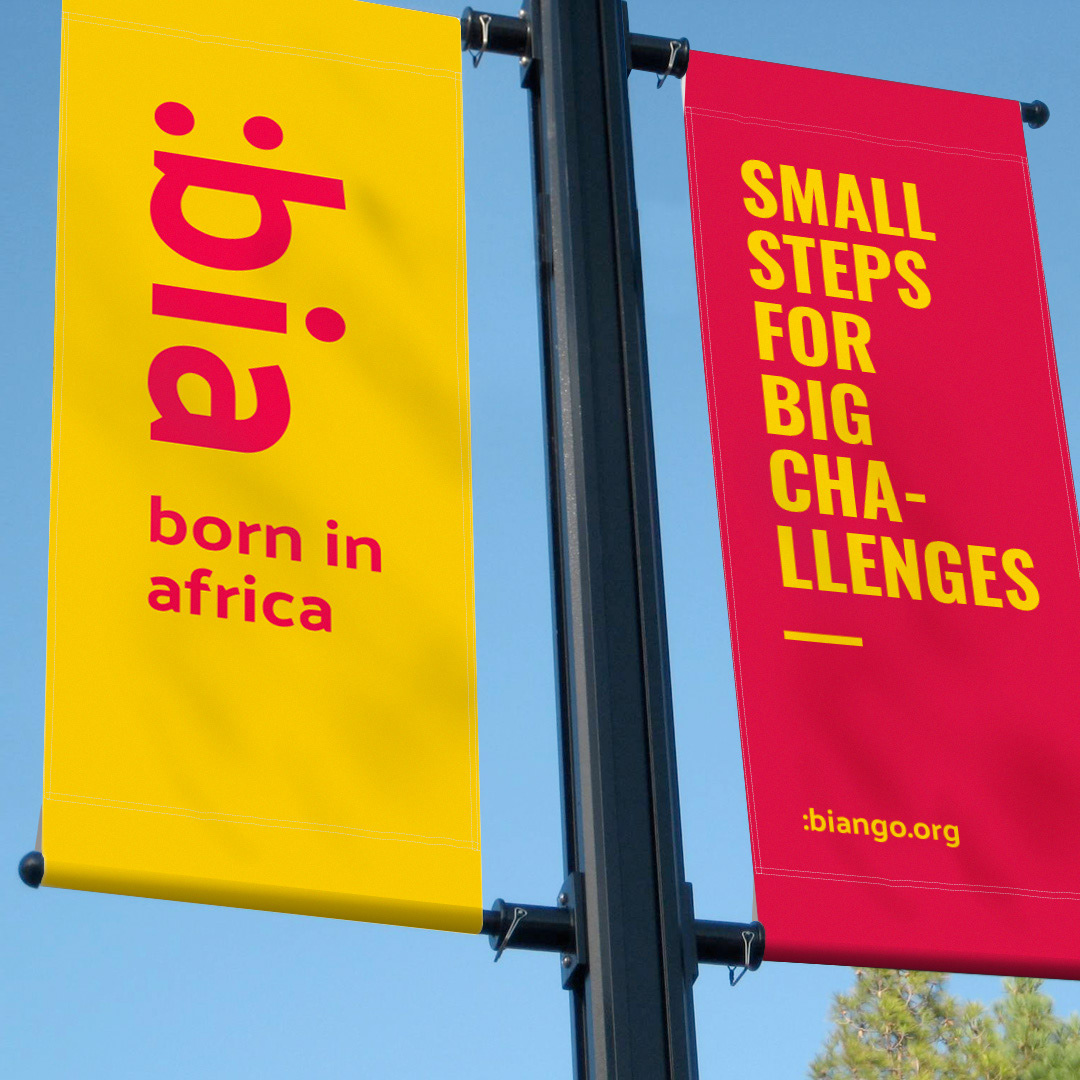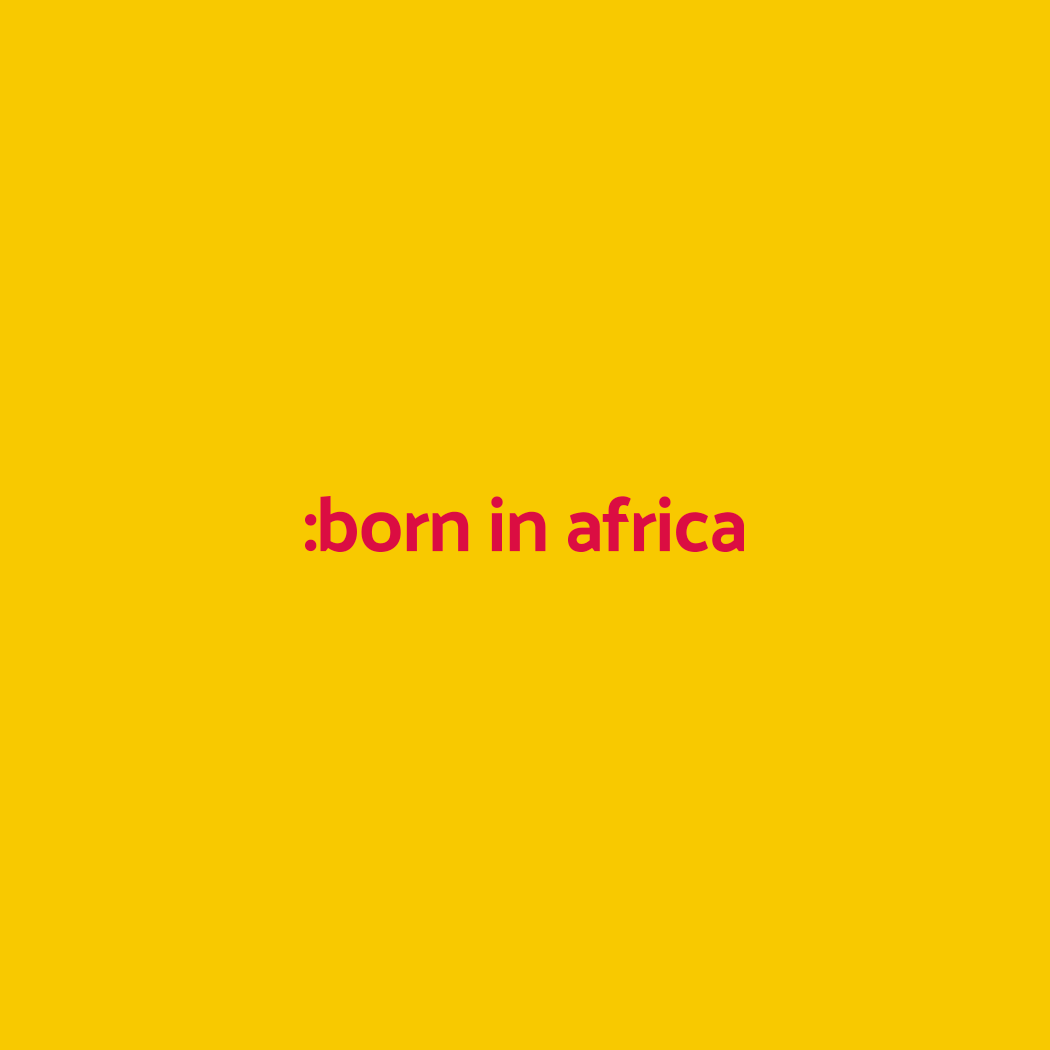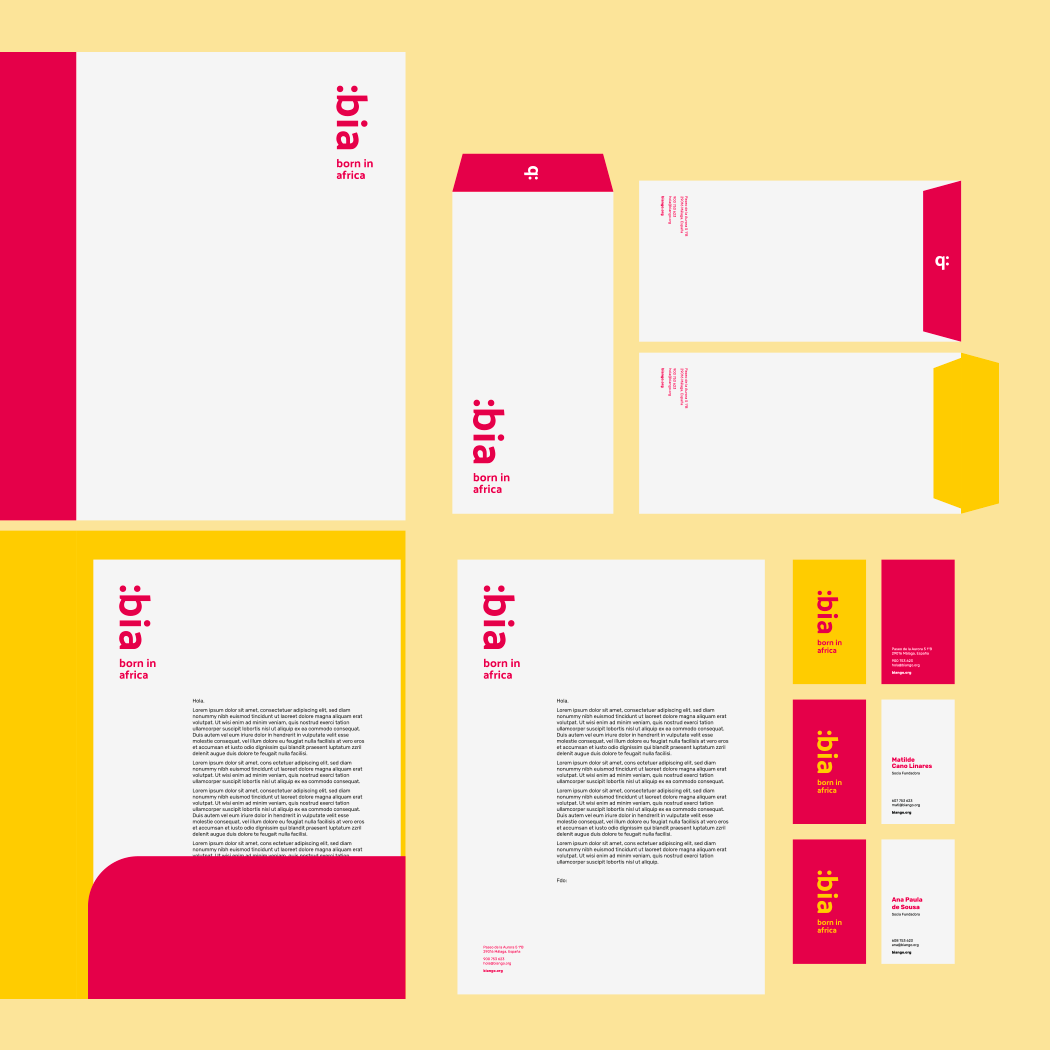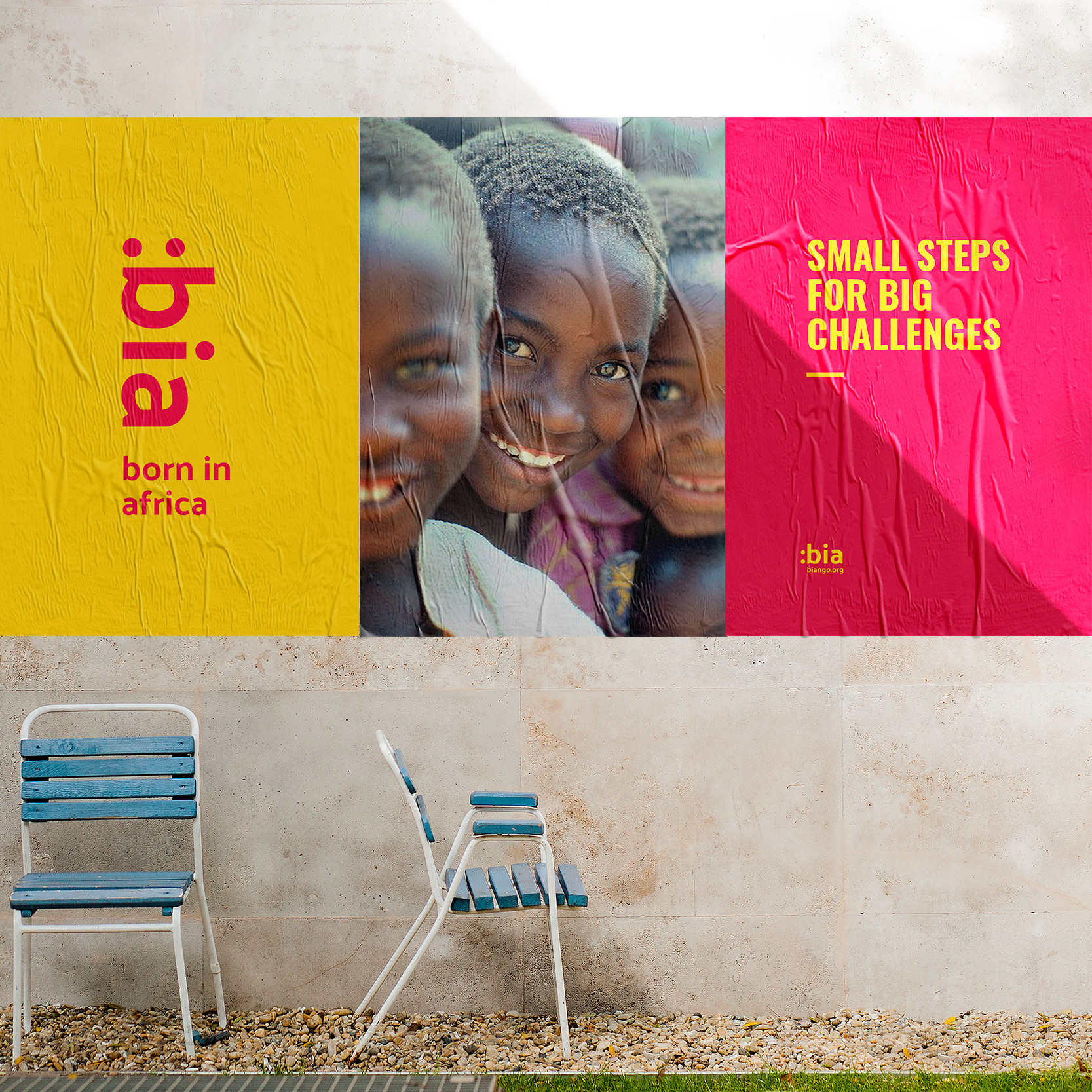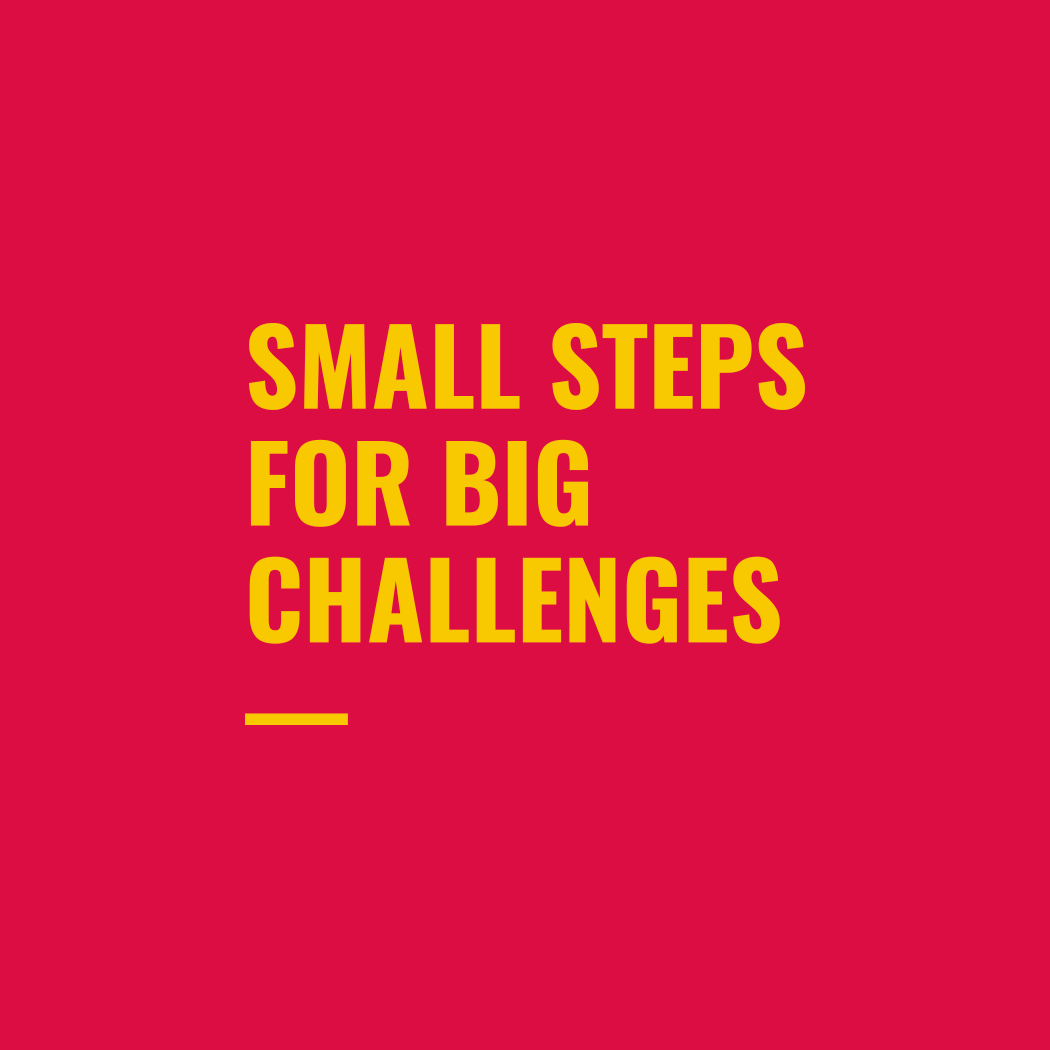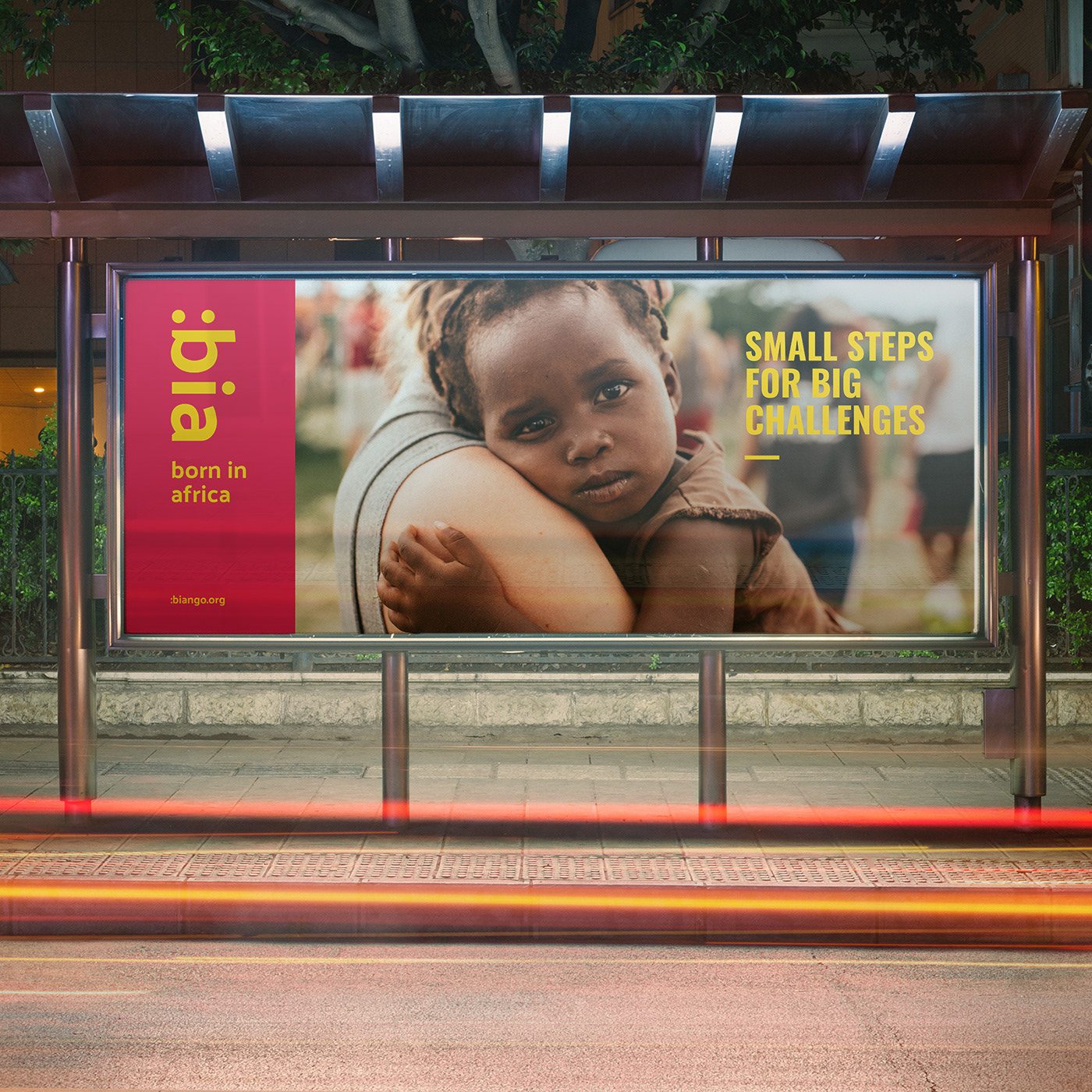
Sistema de identidad visual para :born in africa, ONG que opera entre Uganda y España.
En un territorio saturado de logotipos con continentes africanos y siluetas humanas, se buscó la diferenciación a través de la máxima simplicidad. La imagen a representar a través del logotipo era la de alegría y esperanza y se consiguió hacerlo únicamente con tipografía, reforzada con una dirección fotográfica llena de sonrisas.
Identity visual system for :born in africa, NGO operating in Uganda and Spain.
In a brand territory full of logos of silhouettes and african continents, the goal was the differentiation through simplicity. Hope and joy were the values to enhance and the solution was found with no need of icons, just with the characters of the typography.